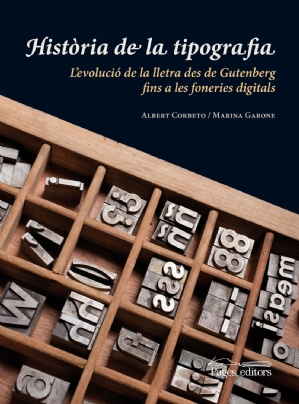
Sin lugar a dudas el historiador e investigador de la imprenta Albert Corbeto se encuentra en una fase creativa excelente. Si no hace mucho nos apabulló con su publicación doble sobre D.B. Updike y la imprenta en España, ahora nos vuelve a dejar sin aliento con Història de la tipografia. L`evolució de la lletra des de Gutenberg fins a les foneries digitals, una obra de la que es coautor junto a la investigadora argentina radicada en México Marina Garone.
Un manual sobre la historia de la tipografía siempre tiene el peligro de caer en lugares comunes y quedarse en los hechos superficiales de la descripción de los diferentes tipos de letra y sus creadores a lo largo de la historia. En este caso tenemos que aplaudir que el relato del desarrollo de la tipografía se encuentre incorporado junto a las condiciones sociales, económicas y culturales de las diferentes épocas por lo que adquiere su pleno sentido como una expresión más del devenir histórico de las diferentes sociedades.
También se ha de destacar que alejándose del enfoque anglosajón clásico que podemos observar en la mayoría de los relatos acerca del desarrollo histórico de los tipos de letras, los autores hacen especial hincapié en incorporar también la producción realizada en España con lo que supone de normalización sobre todo teniendo en cuenta su magnífica etapa de la segunda mitad del siglo XVIII.
En definitiva, un título muy recomendable en el que la historia de la tipografía no es una simple correlación de nombres sino que incorpora un contexto que, sin duda, nos proporcionará un conocimiento profundo de las formas de las letras como expresión cultural de una época.
Història de la tipografia
por Albert Corbeto y Marina Garone